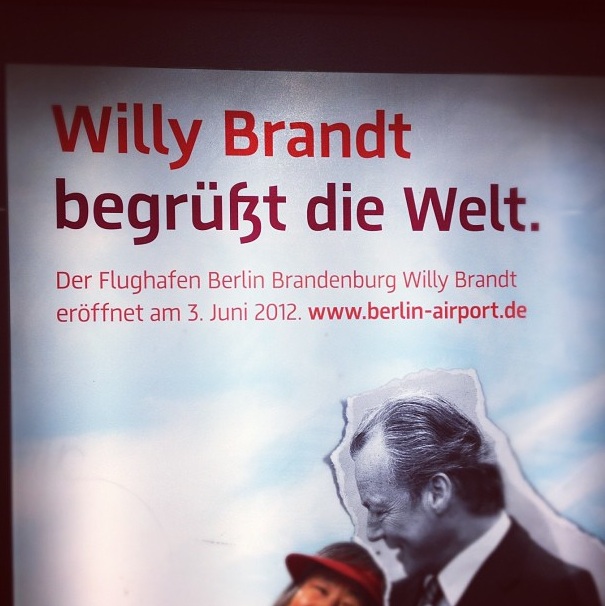
Eszett in der Hausschrift des Flughafens BER
85 Prozent der Betrachter am Flughafen werden erst mal "Willi Brandt begrützt die Welt." lesen.
>> bertel: Das halte ich, mit Verlaub, für Unsinn.
Weiß jemand, was für eine Grotesk das ist?
Die Form ist in dem Fall ein bewusst eingesetztes lokales Markenzeichen als Anspielung auf die Berliner Straßenschilder. Gefällt in diesem Zusammenhang, hat aber ansonsten nix mehr in aktuellen Schriften zu suchen. (da für die Masse der heutigen Leser eher hinder- als förderlich.) Da können sich die »gesunden Conservativen« noch so sehr auf den Kopf stellen.
Wesentliche Aufgabe der Schrift: mithelfen für Orientierung zur Sorgen am Flughafen. So gesehen nicht optimal gelöst dieses „ß“.
Das sei dir zugestanden. Ich halte das ß trotzdem für komplett verunglückt. Eine Schrift, die explizit für einen Flughafen entworfen wurde, muss 100 Prozent Funktion haben und möglichst schnell les- und erfassbar sein. (Wenn sie darüber hinaus noch etwas hübsch ist, schadet das nicht). Das ß wird mit Sicherheit von vielen nicht sofort erkannt werden, weil es nicht der gewohnten Form entspricht (und damit nicht schnell erfassbar ist), ist somit also als Fehler anzusehen.
das ß passt schon, genau aus den gründen die ralf genannt hat und
es ist ja auch nur im deutschen verfügbar. ich glaube nicht das
jemand, der der deutschen sprache mächtig ist, begrützt ließt.
Die dort reichlich zu erwartenden internationalen Gäste werden es sicher nicht sofort erkennen ...
... als B, also Ziel erreicht! ;-)
Die Deutschen, die die Form nicht als ß erkennen, werden auch eher nicht "begrützt" lesen, denn würden sie das ʒ als z erkennen, was für den tz-Irrtum nötig wäre, wäre der Schritt zum korrekten Erkennen des ſʒ auch nicht mehr weit ...
Natürlich ist das alles irgendwie entzifferbar. Aber – ich wiederhole mich da – eine speziell für einen Flughafen entworfene Schrift darf nicht mehrere Schritte bis zum zweifelsfreien Erkennen voraussetzen, das ist kontraproduktiv.
Ich stelle mir gerade die Frage, wie viele Worte im Leitsystem denn tatsächlich ein »ß« benötigen. Und ob es dann überhaupt die relevanten, schnell zu dekodierenden Inhalte betrifft … :-?
Mit der Herangehensweise hätten sie gleich die Arial nehmen können.
Was soll das denn jetzt? Als man dieses Projekt konzipierte, könnten das doch durchaus Gedanken gewesen sein, die gerade zu diesem jetzigen »ß« den Ausschlag gaben.
Es würde mich wundern, wenn eine Schrift für einen Flughafen entwickelt und dabei bewusst ein schlecht erfassbares ß gestaltet wird, weil je eh keine relevanten Informationen ein ß enthalten werden. Das klingt schon sehr an den Haaren herbeigezogen ;-)
Diese Frage hatte sich mir auch gestellt. Ich gehe davon aus, dass es diese Diskussion zwischen Schriftgestalter und Signaletiker/Grafik-Designer bezüglich der ß-Gestaltung gegeben hat. Und dass man sich schließlich aufgrund der wenigen Begriffe, die ein ß innerhalb des Orientierungssystems verlangen, für das Berliner-ß entschieden hat.
Ich könnte mir höchstens vorstellen, dass das als Hommage an der Berliner ß gemacht wurde. Nicht aber weil eh keine relevanten Informationen ein ß enthalten.
Meine Spekulation noch mal konkretisiert:
Ich könnte mir vorstellen, dass es eine Hommage an das Berliner ß werden sollte. Möglicherweise gab es auch einen Plan B. Weil aber keine relevanten Informationen ein ß enthalten, gab es nichts gegen den Wunsch einer Hommage einzuwenden. Also konnte man sich schlussendlich ruhigen Gewissens dazu entschieden. :roll:
War Stefan an dem Designprozess beteiligt?
Ich find’s natürlich wunderbar! Ich glaube auch nicht, daß viele Menschen mit diesem ß Schwierigkeiten haben, und falls Schwierigkeiten auftreten, bedeuten diese höchstens Verzögerungen von Sekundenbruchteilen. Es sei denn natürlich, jemand bleibt stehen, um die schöne Schrift zu bewundern. ;-)
Mir gefällt, dieses Eszett recht gut und auf den Berliner Straßenschildern ließt ja auch niemand Stratze. Aber möglicherweise hat die Schriftart ja auch noch ein „normales“ Eszett welches bei Bedarf genutzt werden kann.
Diese Form ist schon seeeeehr speziell und kommt so gegebenenfalls in der normalen Leseerfahrung vieler Menschen schlicht überhaupt nicht vor …
Warum kommt es denn der »Leseerfahrung vieler Menschen schlicht überhaupt nicht vor«? Wenn dann doch sicher, weil es diese Alternative heute nicht mehr so oft in die gängigen Schriften schafft, oder? Das heißt doch aber nicht, dass man diese nicht im Handumdrehen »lernen« könne, so wie die Spielarten vieler andere Buchstaben auch.